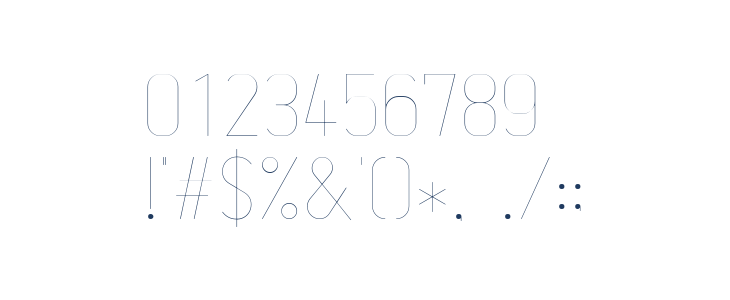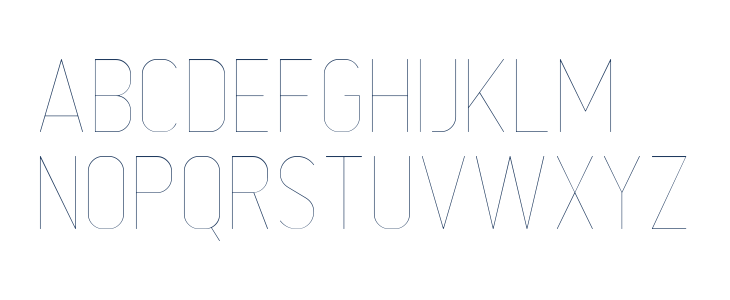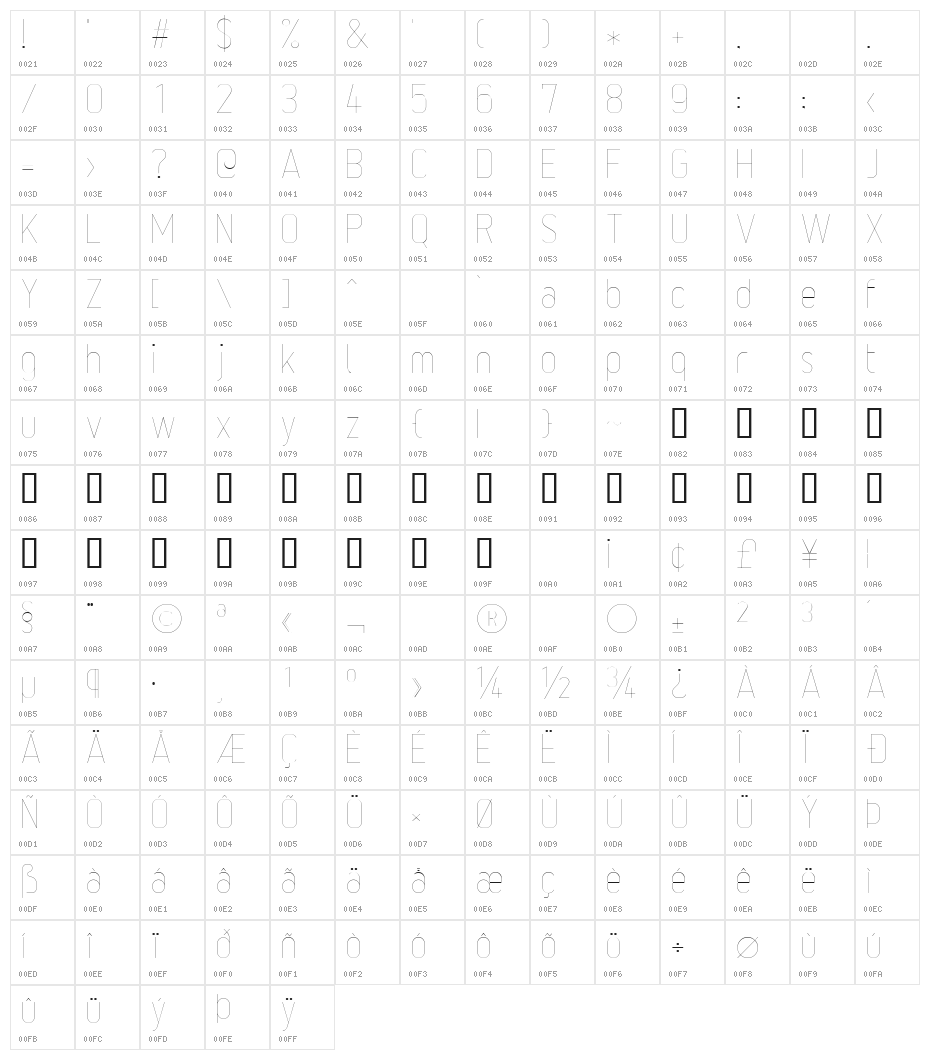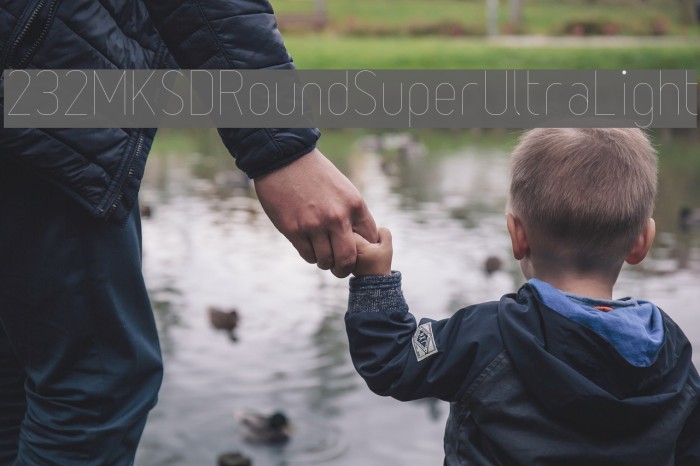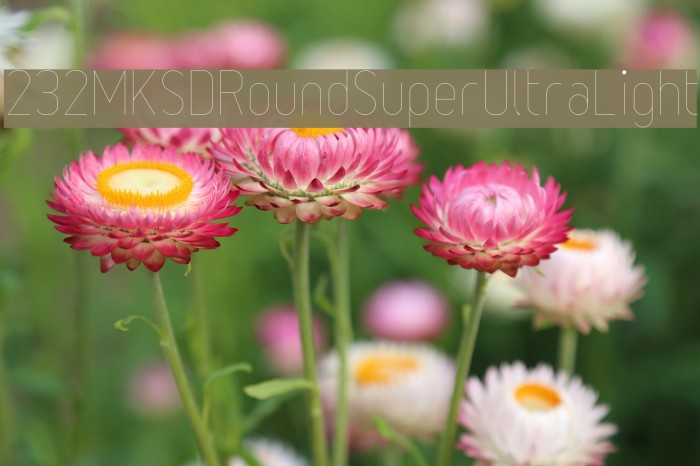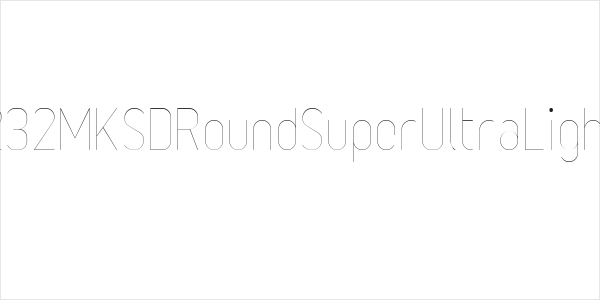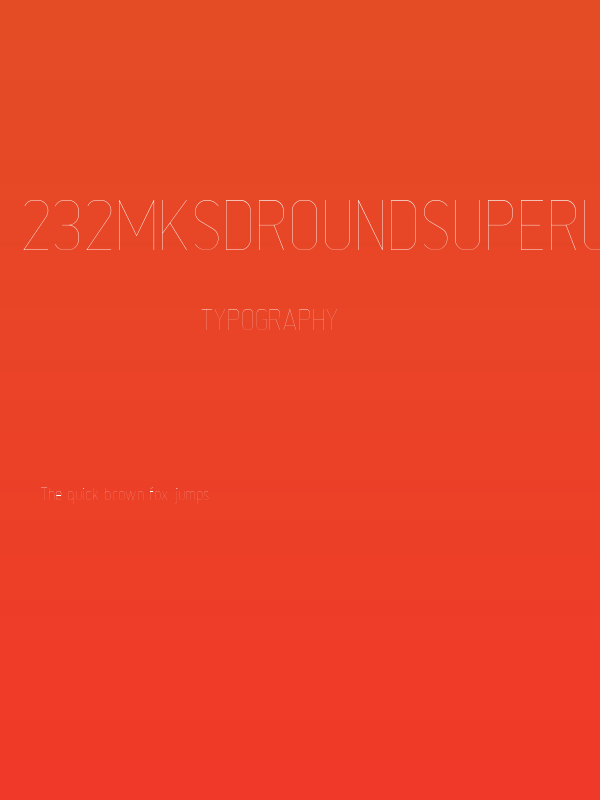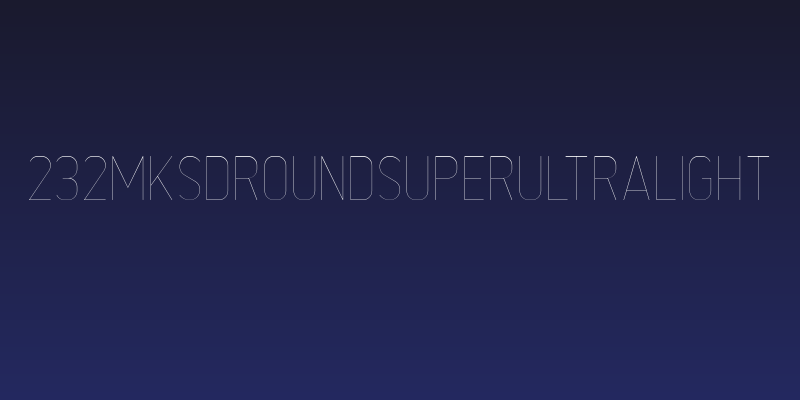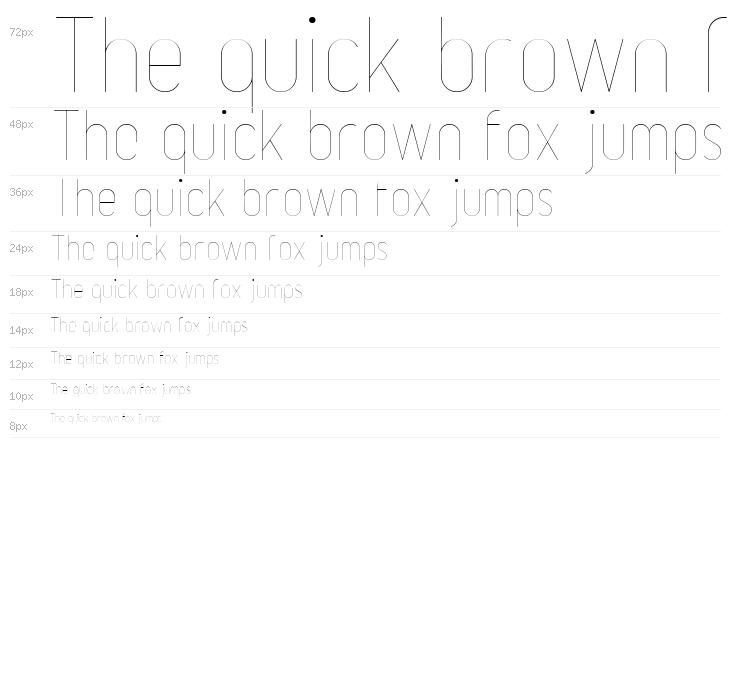
232MKSDRoundSuperUltraLight Font
Fonts by Maniackers Design - www.mksd.jp
| Progetti proposti | Ideal for modern branding, minimalist posters, sleek website headers, and elegant invitations. |
| Autore | Fonts by Maniackers Design - www.mksd.jp |